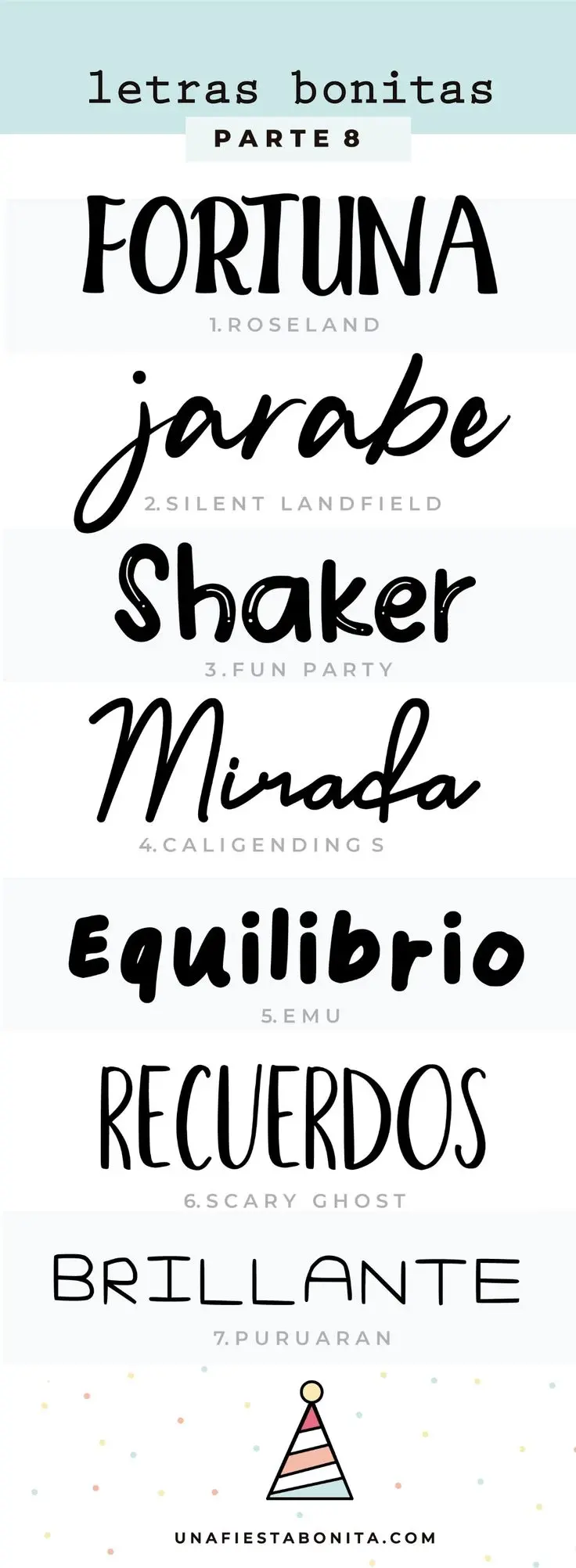
La tipografía juega un papel crucial en el diseño de anuncios. Una fuente adecuada puede transformar un anuncio común en una pieza cautivadora, mientras que una elección incorrecta puede arruinarlo por completo. Por eso, saber descargar tipografía para anuncios es una habilidad esencial para cualquier diseñador o marketer.
Mejores Sitios para Descargar Tipografía para Anuncios
Existen numerosos sitios web que ofrecen fuentes gratuitas y de pago. A continuación, exploramos algunos de los más populares y confiables, destacando sus ventajas y desventajas para ayudarte a descargar tipografía para anuncios que se ajusten a tus necesidades:
| Sitio Web | Características | Ventajas | Desventajas |
|---|---|---|---|
| Google Fonts | Gran variedad de fuentes de código abierto. Fácil descarga e instalación. | Fuentes de alta calidad, libres de regalías y aptas para uso comercial. | Menos opciones de fuentes inusuales o de diseño más específico. |
| Dafont | Más de 60.000 fuentes, incluyendo opciones gratuitas y de pago. | Amplia biblioteca, opciones para uso comercial y personal. | La gran cantidad de opciones puede dificultar la búsqueda. |
| Font Squirrel | Fuentes gratuitas para uso comercial. | Fuentes originales y de estilo único, ideales para proyectos creativos. | Biblioteca relativamente pequeña en comparación con otras opciones. |
| 1001 Fonts | Amplia gama de fuentes categorizadas, incluyendo opciones gratuitas para uso comercial. | Facilidad para buscar y filtrar por estilo y categoría. | Puede incluir algunas fuentes de calidad inferior. |
| MyFonts | Más de 130.000 fuentes, algunas gratuitas. | Gran variedad de estilos, herramienta «What the font» para identificar fuentes. | Necesidad de filtrar la búsqueda para encontrar las opciones gratuitas. |
| UrbanFonts | Variedad de fuentes gratuitas para uso personal y comercial. | Herramienta de previsualización, búsqueda por categoría. | Similar a Dafont en la gran cantidad de opciones. |
| Font Diner | Fuentes vintage, ideal para diseños retro. | Estilo único, perfecto para proyectos con temática nostálgica. | Biblioteca pequeña, enfocada en un estilo específico. |
| All Free Font | Más de 2000 fuentes gratuitas en formato Truetype. | Gran cantidad de fuentes en un solo lugar. | La navegación puede ser un poco confusa. |
| FontFabric | Fuentes gratuitas, opción para crear fuentes personalizadas. | Posibilidad de diseño personalizado, fuentes de alta calidad. | Menos fuentes gratuitas en comparación con otras plataformas. |
| FontZone | Más de 50.000 fuentes gratuitas. | Amplia biblioteca, organización por categorías y alfabética. | Similar a Dafont en la gran cantidad de opciones. |
| ByPeople | Recursos para diseñadores, incluyendo fuentes gratuitas para uso comercial. | Fuentes de alta calidad, aptas para uso comercial. | Menos cantidad de fuentes gratuitas que otras plataformas. |
| FontBundles | Fuentes gratuitas para uso comercial, organizadas por temáticas. | Paquetes de fuentes temáticas, facilitando la búsqueda. | Requiere iniciar sesión para descargar. |
| Font River | Fuentes gratuitas para uso personal y comercial. | Organización por categoría y alfabeto, filtro de licencia. | Menos variedad de fuentes que otras plataformas. |
| Free Typography | Fuentes gratuitas de diseñadores independientes. | Fuentes únicas y exclusivas. | Menos cantidad de fuentes que otras plataformas. |
| AllFont | Más de 9000 fuentes gratuitas. | No requiere registro, organización temática y alfabética. | Similar a otras plataformas en la gran cantidad de opciones. |
Recuerda siempre verificar la licencia de uso de cada fuente antes de descargar tipografía para anuncios, especialmente para uso comercial. Algunas fuentes gratuitas pueden tener restricciones en su uso.
Consejos para Elegir la Tipografía Adecuada para tus Anuncios
- Considera tu público objetivo: ¿A quién te diriges? Una fuente elegante puede no ser adecuada para un público joven, mientras que una fuente informal puede resultar inapropiada para un producto de lujo.
- Define el tono y el mensaje: ¿Quieres transmitir sofisticación, alegría, seriedad, o informalidad? La tipografía debe reflejar el mensaje de tu anuncio.
- Lee el anuncio con la tipografía elegida: ¿Es fácil de leer? ¿Se ve bien? Es importante que la tipografía sea legible y estéticamente agradable.
- Prueba diferentes combinaciones: Experimenta con diferentes fuentes para el título y el cuerpo del texto. Una buena combinación puede mejorar significativamente el impacto visual de tu anuncio.
- Respeta la jerarquía visual: Usa diferentes tamaños y pesos de fuente para destacar los elementos más importantes del anuncio.
- Mantén la consistencia: Una vez que hayas elegido una fuente, utilízala de forma consistente en todos tus materiales de marketing.
Descargar tipografía para anuncios es un proceso simple una vez que se conoce el procedimiento. Al seguir estos consejos y explorar las numerosas opciones disponibles, podrás encontrar la fuente perfecta para que tus anuncios sean visualmente atractivos y efectivos.